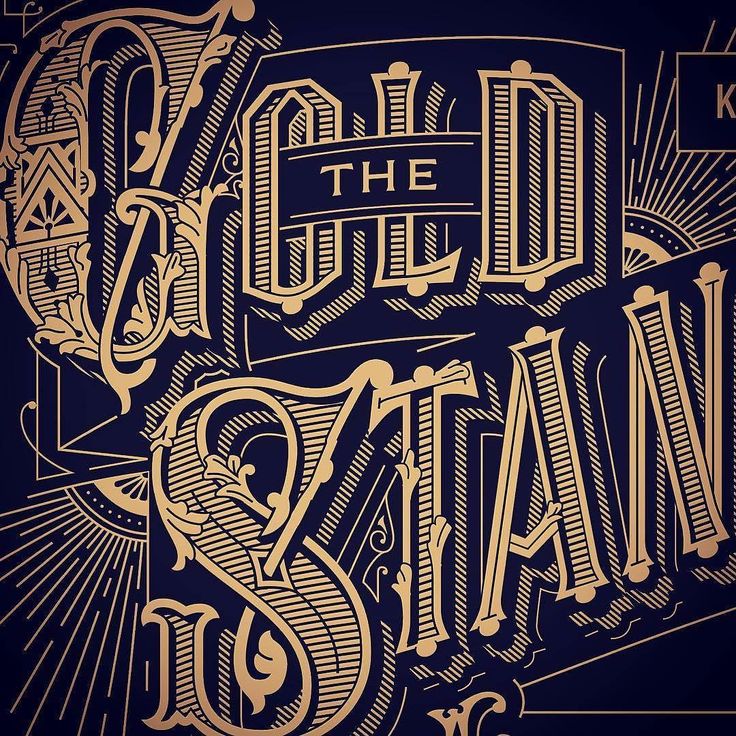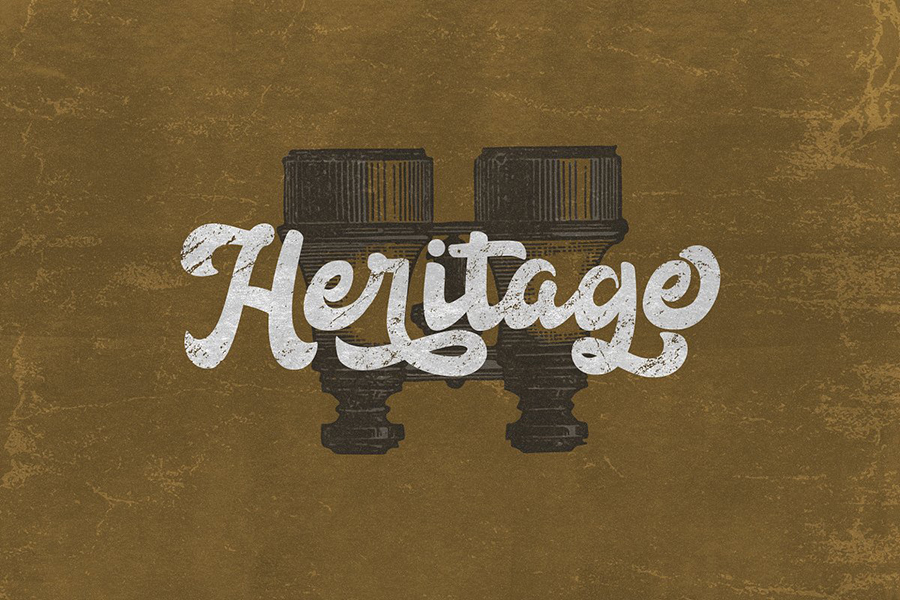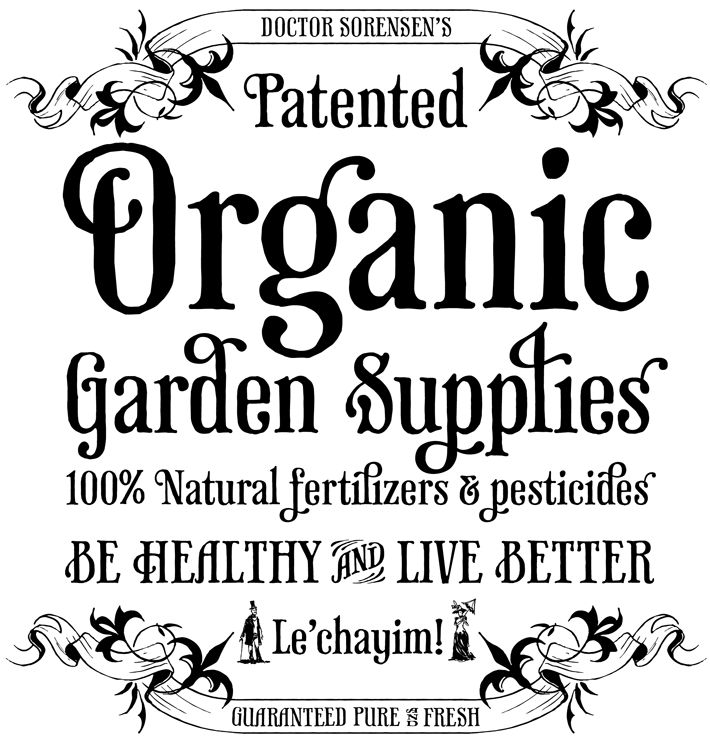
21 лучший ретро-шрифт
21 лучший ретро-шрифт Вы ищете лучшие шрифты, чтобы придать вашим проектам ностальгический, винтажный вид? Ретро-шрифты — идеальный инструмент, чтобы сделать вашу работу вневременной и добавить желаемую текстуру и возраст.
1. Wicked Hearts Retro Serif
Wicked Hearts — это массивный шрифт с засечками и краем — классная современная интерпретация классического ретро-шрифта. Wicked Hearts наполнен множеством альтернатив и лигатур, чтобы действительно оживить его и предоставить вам широкий спектр возможностей для настройки.
2. Highbinder Display Font
Highbinder Display Font — новейший шрифт от Vintage Type Co., вдохновленный типографикой эпохи запретов. Шрифт имеет чистый и грубый стиль и идеально подходит для ретро-логотипов, постеров, макетов и многого другого!
3. Винтажные шрифты Rumble Brave
В этой коллекции вы найдете 3 варианта ретро-шрифта: с засечками, рукописный и дингбат. Три комбинации шрифтов отражают концепцию классического дизайна викторианской эпохи. Этот шрифт сочетает в себе роскошь, элегантность и стиль!
4. Семейство шрифтов Halau Serif
Представляем замечательное современное семейство шрифтов середины века с пятью вариантами ширины — Halau Serif. Классический шрифт с засечками середины века с характерным мультяшным видом. Идеально подходит для ваших летних проектов, поиграйте с ним и получите действительно классный стиль ретро-надписей.
5. Valent — шаблоны шрифтов и логотипов
Valent — смелый шрифт для смелых заявлений! Благодаря толстому корпусу и очаровательным засечкам, Valent идеально подходит для винтажных ретро-логотипов и дизайнов, а также для брендинга проектов, упаковки и крупных журнальных заголовков.
6. Pacifica
Pacifica — это рукописный элегантный полужирный шрифт для декоративной типографики, вдохновленный ретро-американской типографикой брендинга. Шрифт поставляется с различными вариациями — заполненными, выделенными или нажатыми. Идеально подходит для ретро-заголовков, вывесок, логотипов, принтов и т. д.
7.
Java Heritages + ExtrasJava Heritages Typeface — это многослойное семейство шрифтов с функциями открытого типа, вдохновленное ретро-вывесками с уникальными декоративными формами.
8. Charcuterie
Charcuterie — это семейство из десяти различных, но связанных между собой ретро-шрифтов, многие из которых имеют свои собственные семейства шрифтов, а также три декоративных/орнаментальных гарнитуры. Этот амбициозный, но доступный набор предлагает практически бесконечную серию комбинаций, позволяющих составить вкусную тарелку ингредиентов для каждого проекта.
9. Saveur Sans
Дизайн Saveur Sans вдохновлен ар-деко и французскими кафе. Это семейство дисплеев имеет четкие, простые формы букв, которые кажутся современными, но в то же время имеют стиль ретро в стиле ар-деко. Это семейство может добавить изысканности любому макету, будь то печать или онлайн.
10. Семейство Antone
Представляем семейство ретро-шрифтов Antone, включающее 7 версий шрифтов.
Характер чистой версии этого шрифта смелый, сильный, но элегантный, в то время как грубая и блочная версия подходит для винтажного и ретро стиля.
11. Шрифт Beauford
Представляем новый шрифт для дисплеев в стиле ретро, он называется Beauford. Вы можете использовать его для различных целей: логотипы, заголовки, футболки, фирменные бланки, вывески, этикетки, плакаты и т. д. «Ячмень». Они работают вместе, чтобы дать вам идеальную ретро-этикетку, которую вы разработали.
13. Коллекция шрифтов Aviator
Коллекция шрифтов Aviator представляет собой набор из четырех разных ретро-шрифтов в 100% потрясающем ретро-стиле! И это еще не все — 52 винтажные иллюстрации для создания логотипов и потрясающие инструменты — средство создания винтажных значков!
14. Stamp & Co — шрифт Vintage Stamp
Добро пожаловать в высоко детализированный текстурированный шрифт в стиле ретро.
15. Шрифт Nebula
Современный шрифт в стиле ретро, в котором используются простые стилизованные линии с закругленными концами, которые кажутся капающими.
Чаще всего он используется для создания привлекательных чистых иллюстраций и значков. Он также известен как «быстрый стиль», потому что создает иллюзию движения изображения!
16. Винтажный шрифт Hotel Royal
Hotel Royal — это ретро-шрифт, вдохновленный шрифтами, которые использовались для старинных гостиничных этикеток первой половины 20-го века.
17. Paneuropa Retro
Paneuropa Retro — это семейство геометрических, чистых и универсальных рето-шрифтов. Paneuropa была переосмыслением знаменитой Futura Пола Реннера — она была немного уже, с другими пропорциями и окончаниями букв.
18. Merchant — Vintage Dry Brush Font
Немного ретро и немного жестковатый, этот шрифт имеет нужное количество текстуры с тонким краем сухой кисти.
19. Семейство винтажных шрифтов Nordin
Семейство винтажных шрифтов Nordin включает 4 шрифта в стиле ретро. Просто используйте свое воображение и некоторые дополнительные возможности графического дизайна, и ваш проект станет более живым и будет выглядеть лучше, чем когда-либо, с семейством шрифтов Nordin.
20. Rustic Jack — A Vintage Font Duo
Шрифт имеет немного грубый и ретро-налет, что делает его идеальным для всех видов винтажных логотипов и брендинга.
21. Старая пишущая машинка Брайтона — Шрифт
«Старая пишущая машинка Брайтона» — это простой ретро-шрифт, созданный из букв, напечатанных на старой и запыленной пишущей машинке. Вы все знаете эти винтажные пишущие машинки и их типичные «прихватки», «прихватки». Этот шрифт вернет вам это ощущение к вашему компьютеру даже без звука «прихватки».